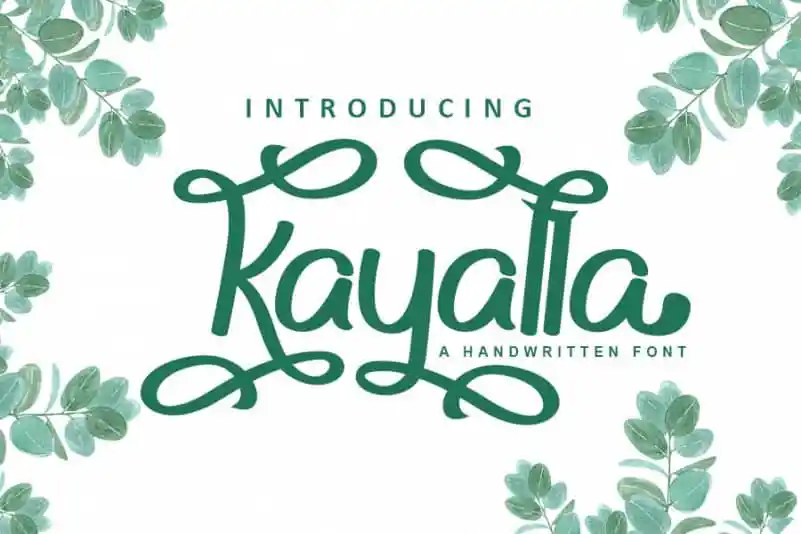
Kayalla Script Font – Download Grátis
Kayalla Script Font é uma elegante fuente escrita a mão que traz um toque delicado à sua próxima criação visual. Seu charme suave e delicado fazê-lo se destacar sob qualquer cenário, especialmente nas ocasiões mais significativas como festas de casamento e cartões de agradecimento. Seu estilo perfeito para personalizar cartazes de boas-vindas, lembrancinhas de aniversários, mensagens pessoais e até mesmo as identidades das empresas – Kayalla Script Font oferece um toque único e artesanal que deixará sua produção gráfica ainda mais ressaltada. Se você está procurando por uma fonte escrita a mão perfeita para enriquecer seu design com elegância e delicadeza, Kayalla Script Font é um excelente investimento.